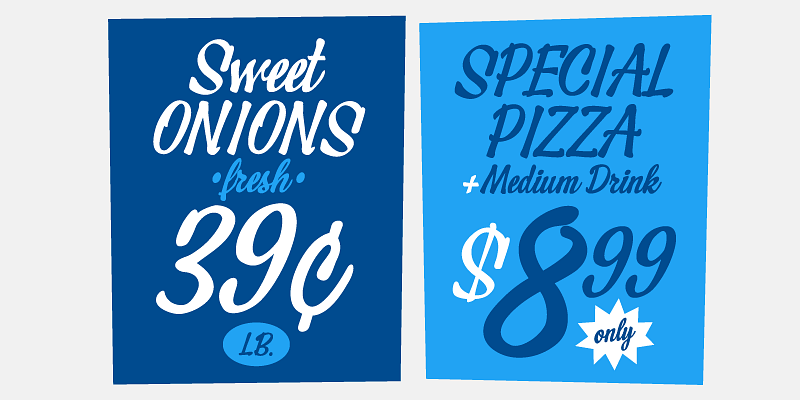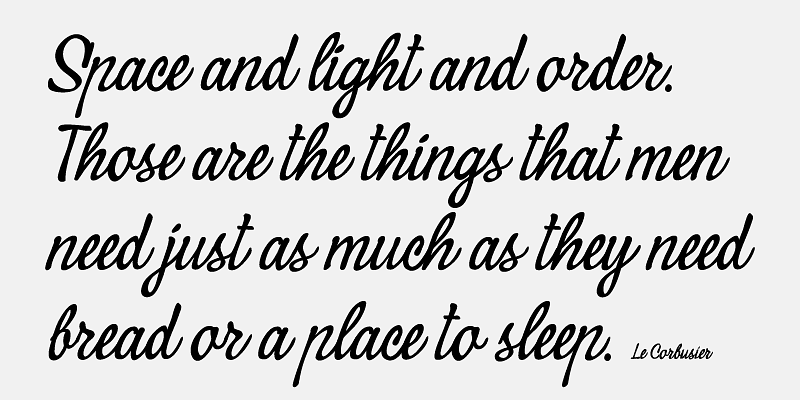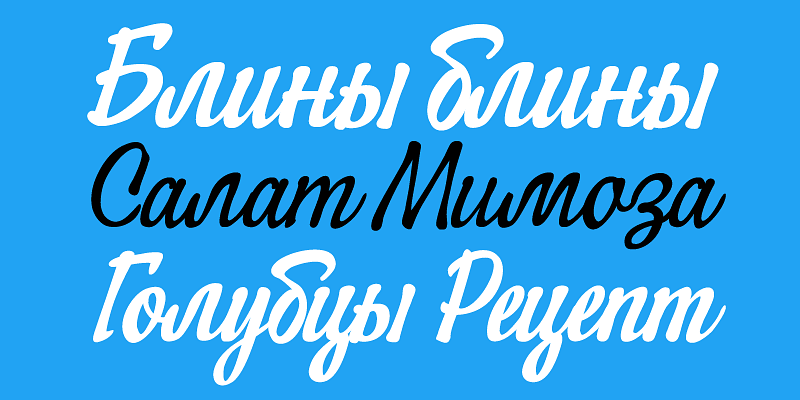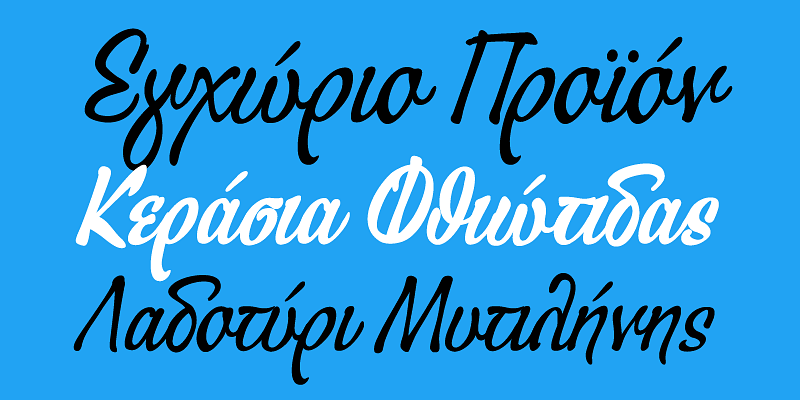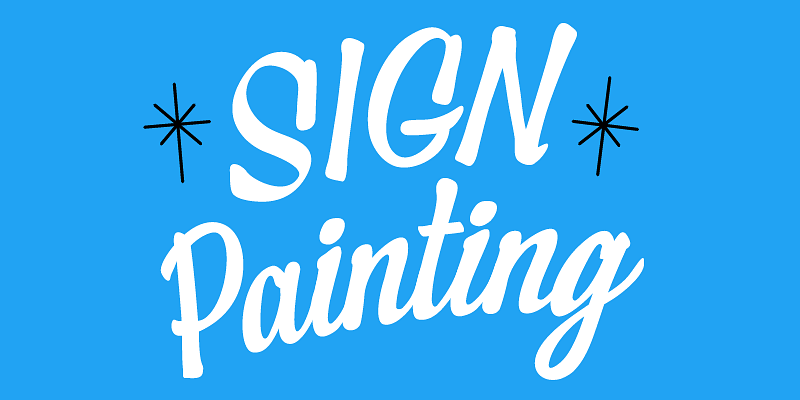
PF Signskript は、数年間オフラインの保管庫と印刷カタログの中に保管されていましたが、まだ購入可能です。PF Signskript は、最終的に再リリースされ、完全に更新され、アップグレードされた貴重な 3 つのタイポグラフィーの逸品の一部です。一流の書道家、書体デザイナー、イラストレーターである Vladimir Radibratović によってデザインされたこの三部作のスクリプト書体は、最近当社のデザインチームによってラテン語、ギリシャ語、キリル文字を完全にサポートするように改良されました。
2002 年に初めてリリースされたこの書体は、人間味のある手作りの雰囲気を表しています。特にカジュアルでナチュラルなコンテキスト内でエクセルを意識してデザインされた PF Signskript のノスタルジックな魅力は、スーパーマーケットの棚にあるブランド、ワインのラベル、パッケージ、引用符、文房具、ヴィンテージのレタリングなどで人気のこの書体に注目を集めています。